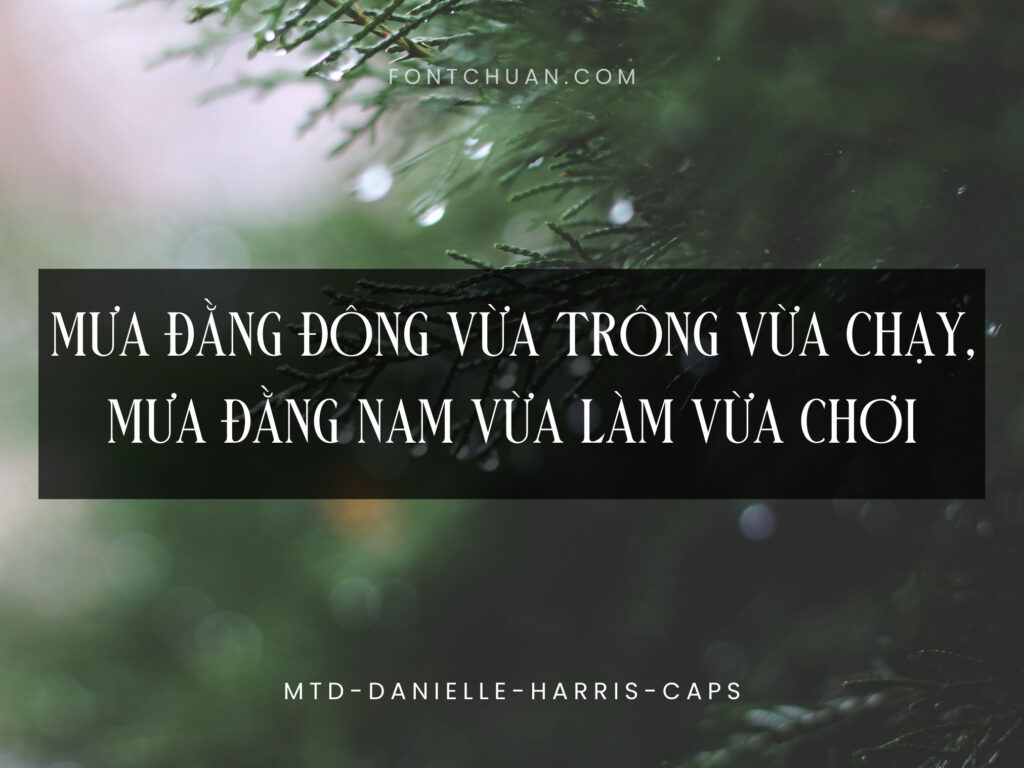
Font MTD Danielle Harris Caps là một Font Serif thanh lịch, được thiết kế bởi Letterhend Studio và đã được Việt hóa bởi Mộc Hạ. Font này hỗ trợ đầy đủ tiếng Việt cùng hơn 90 ngôn ngữ khác, mở rộng khả năng ứng dụng trong các thiết kế đa ngôn ngữ. Đây là một trong những phông chữ được cộng đồng thiết kế đánh giá cao và sử dụng trong nhiều dự án sáng tạo, đáp ứng nhu cầu đa dạng của người dùng.
MTD Danielle Harris Caps nổi bật với các đường nét tinh tế và hiện đại, tạo cảm giác sang trọng và chuyên nghiệp. Font rất phù hợp cho các thiết kế logo, tiêu đề, bao bì sản phẩm, thiệp mời và các ấn phẩm đòi hỏi sự trang nhã và độc đáo. Các ngành nghề phù hợp bao gồm quảng cáo, giáo dục và công nghệ. Font này cũng lý tưởng cho các sự kiện như Tết, Giáng sinh, Valentine và các lễ hội khác.